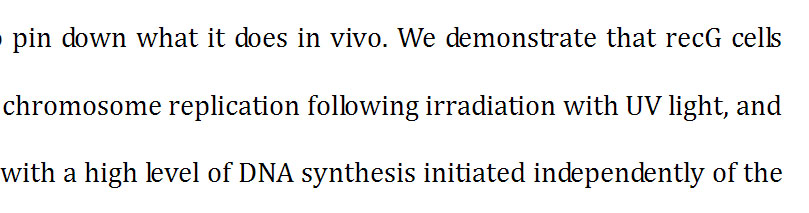
Word - Ligaturen
warum stellt Word eigentlich keine Ligaturen dar?
Gibt es noch weitere derartige Dinge, die Word falsch macht?
Wenn du dein Beispielbild mal etwas genauer anschaust, siehst du („Ty“), dass Word auch nicht unterschneidet.
meiner Erfahrung nach hat Word auch eigene Vorstellungen von normalen Wortabständen und Absatzformatierungen. Und Word verkleinert Bilder beim Import nach Gusto (gerne naheliegende Werte wie 87,23%) und ohne erkennbaren Platzmangel.
Das hatten wir doch vor kurzem schon mal, oder? Word verkleinert eingefügte Bilder immer dann, wenn sie nicht in den Seitenspiegel passen. Wenn sie kleiner sind, dann bleibt die Größe eigentlich unangetastet (zumindest bei 2003).
Mit dem Kerning hat M$ sich selber ein Bein gestellt. Da gibt es nämlich »Kompatibilitätsprobleme« mit neuen Fonts und alter Software bzw. alten Fonts und neuer Software. Cambria auf 2003 mit aktiviertem Kerning sieht z.B. so aus:
In Word2007 hingegen ist das Kerning sauber. Word hat aus diesem Grund auch in Word2007 das Kerning deaktiviert um die Benutzer nicht zu verunsichern. Warum das nicht von vorn herein anständig gelöst wurde, weiß ich auch nicht.
Und Ligaturen gehen einfach nicht automatisch. Obwohl Microsoft ja ganz aktiv bei OpenType dabei ist haben sie der Implementierung anständiger OpenType-features keine Priorität eingeräumt. Man kann sehen wie lange das alleine bei OpenOffice dauert, wo das schon lange angemeckert wurde. Es sollte eigentlich in Version 3 kommen, soweit ich es sehen kann ist die Implementierung allerdings auch dort noch nicht erfolgt. In Word steht es wohl auf der Liste und man kann hoffen, daß es in der nächsten Version kommt, ich habe aber meine Zweifel.